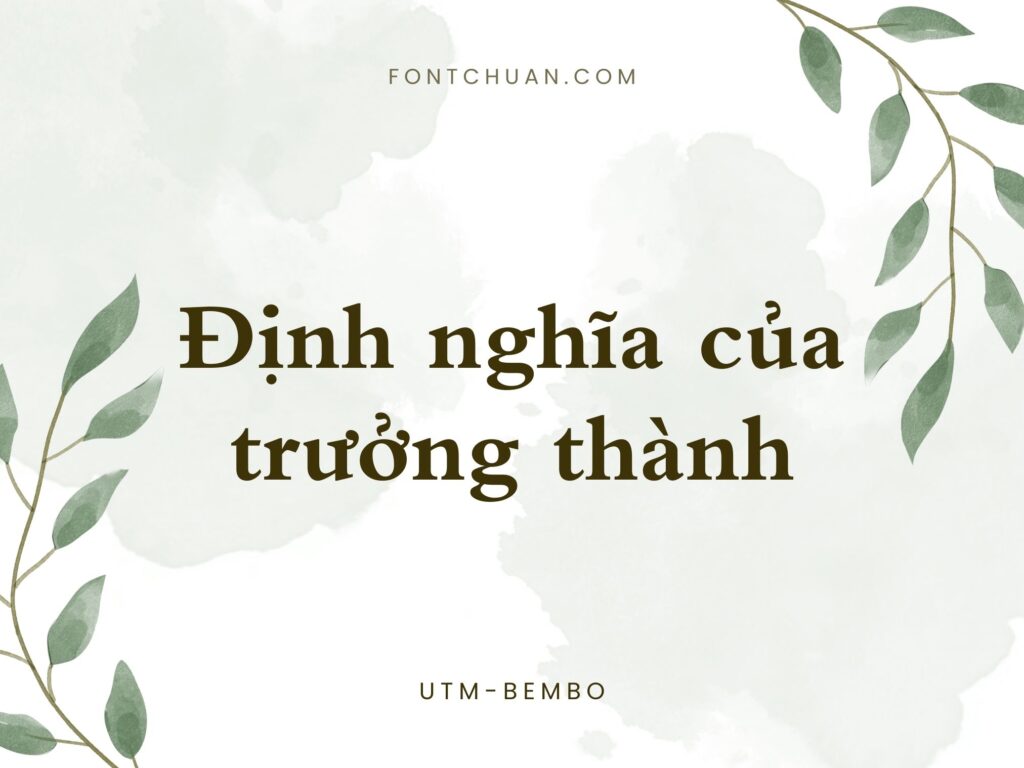
Font UTM Bembo Việt Hóa
UTM Bembo là phiên bản Việt hóa của font chữ Bembo, một kiểu chữ serif cổ điển thuộc nhóm humanist, ban đầu được thiết kế bởi Francesco Griffo vào năm 1495 và được Stanley Morison phục hồi vào năm 1929. Font này nổi bật với các đường nét thanh lịch, độ tương phản nhẹ nhàng giữa các nét dày và mỏng, cùng với chân chữ tinh tế, tạo nên vẻ đẹp trang nhã và dễ đọc. Phiên bản Việt hóa đã được thực hiện, hỗ trợ đầy đủ tiếng Việt cùng hơn 100 ngôn ngữ khác. Đây là một trong những font được cộng đồng thiết kế sưu tầm và chọn lọc nhằm đáp ứng nhu cầu đa dạng trong thiết kế.
UTM Bembo có cấu trúc chữ với các nét mềm mại và tỷ lệ cân đối, tạo nên sự hài hòa và dễ đọc. Font này phù hợp cho các ứng dụng như thiết kế sách, tạp chí, tài liệu học thuật, thiệp mời và các ấn phẩm in ấn yêu cầu sự trang trọng và chuyên nghiệp. Các ngành nghề như quảng cáo, giáo dục, công nghệ và bất động sản có thể tận dụng UTM Bembo để tạo điểm nhấn độc đáo trong thiết kế.